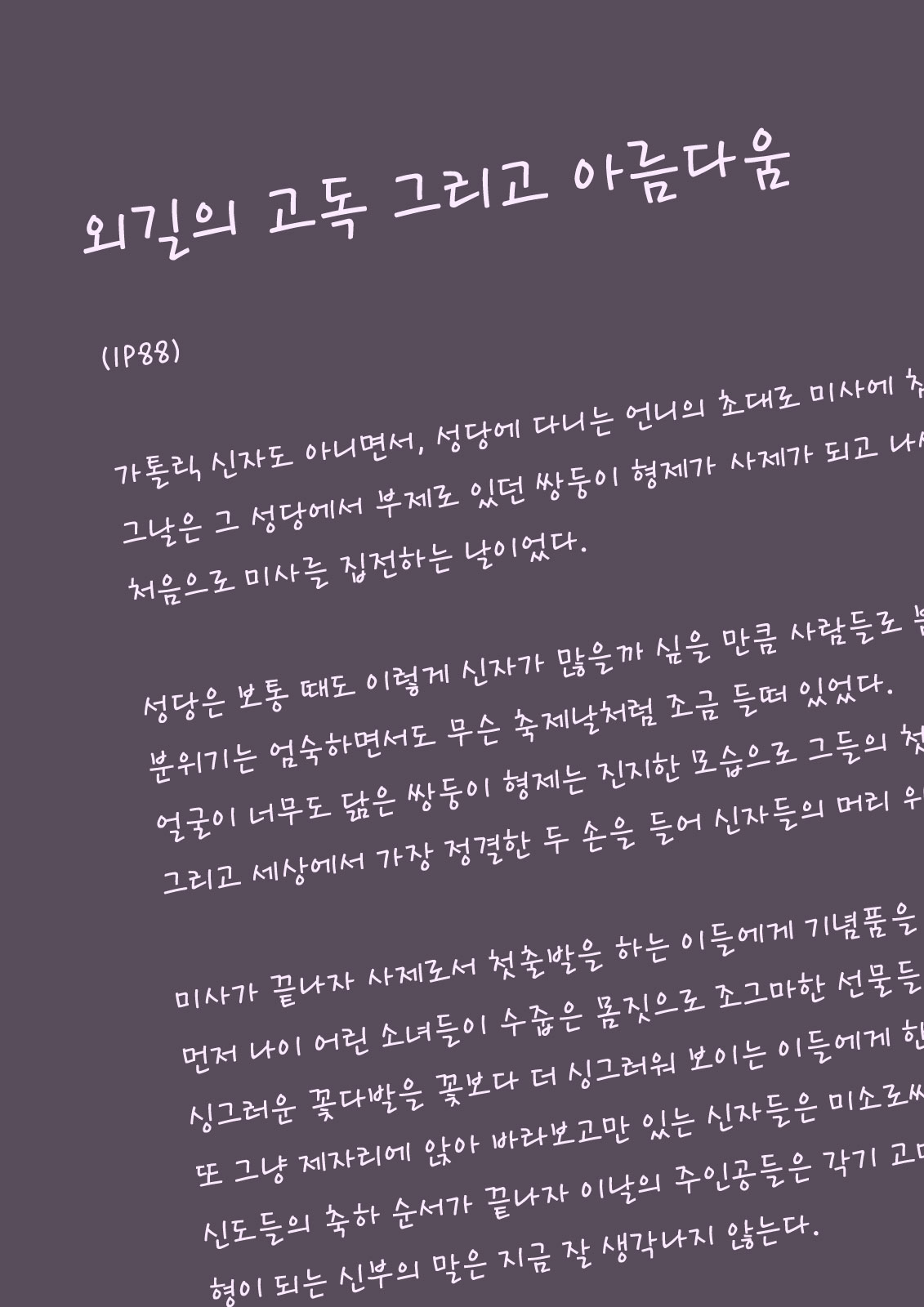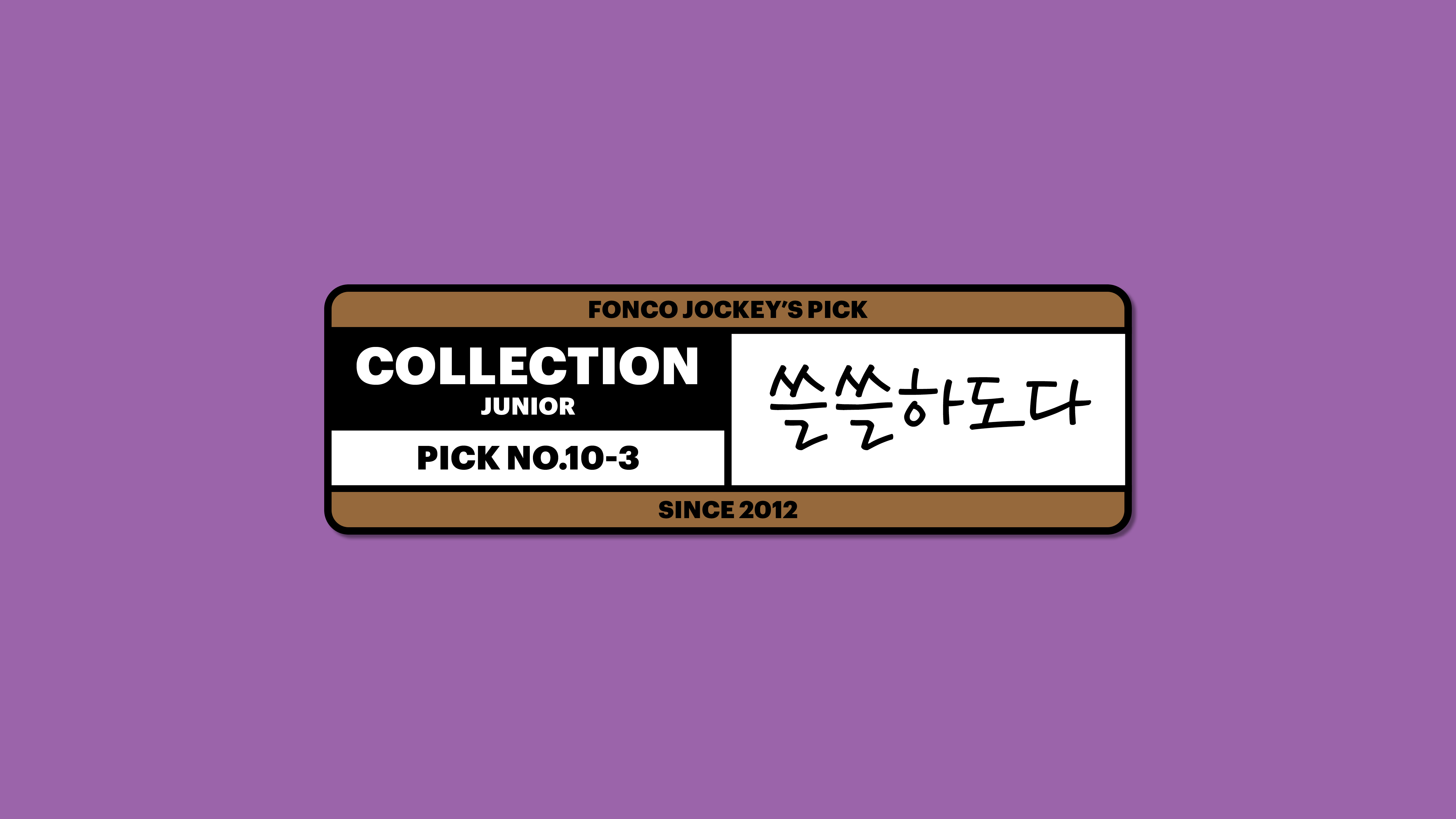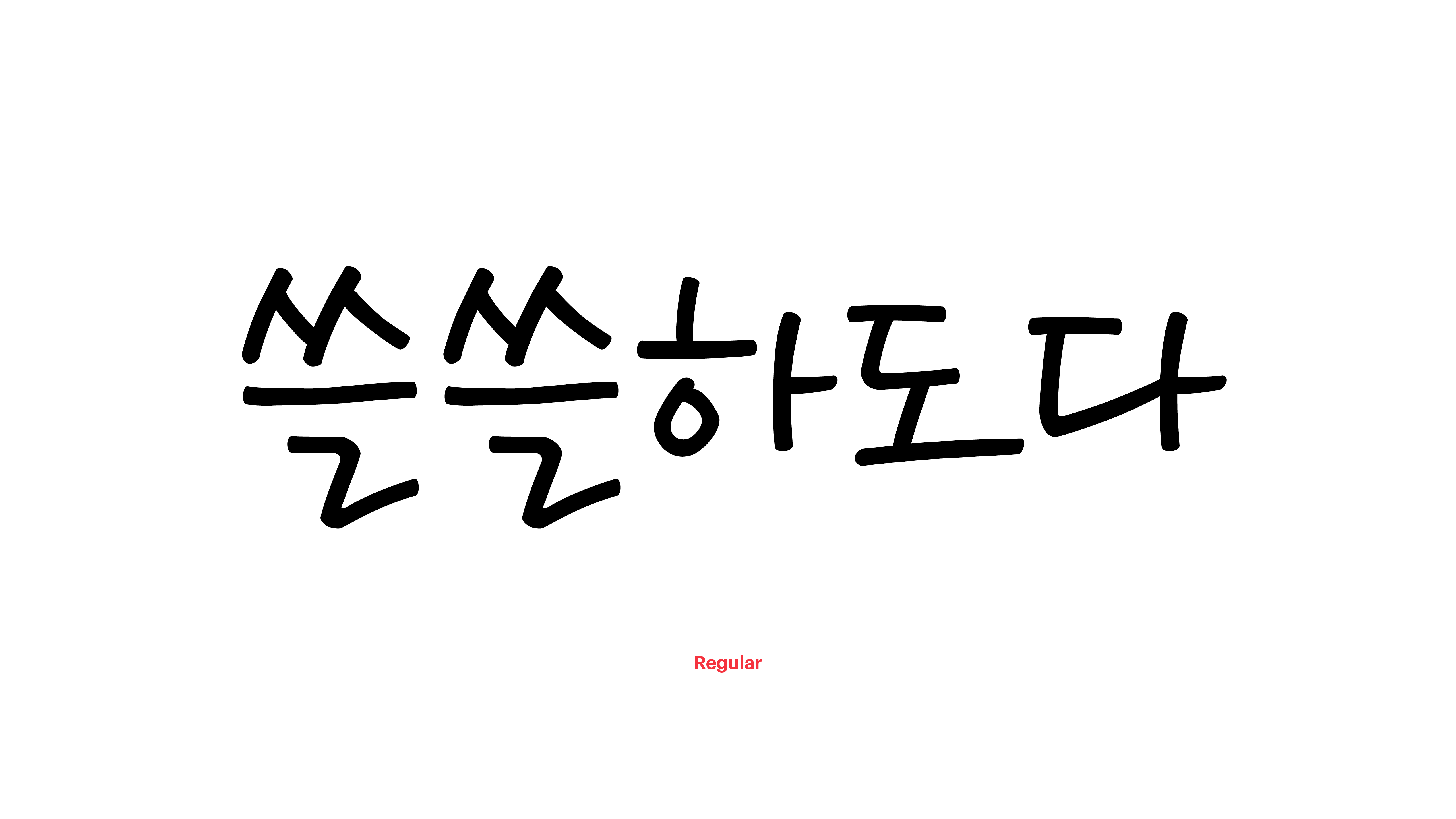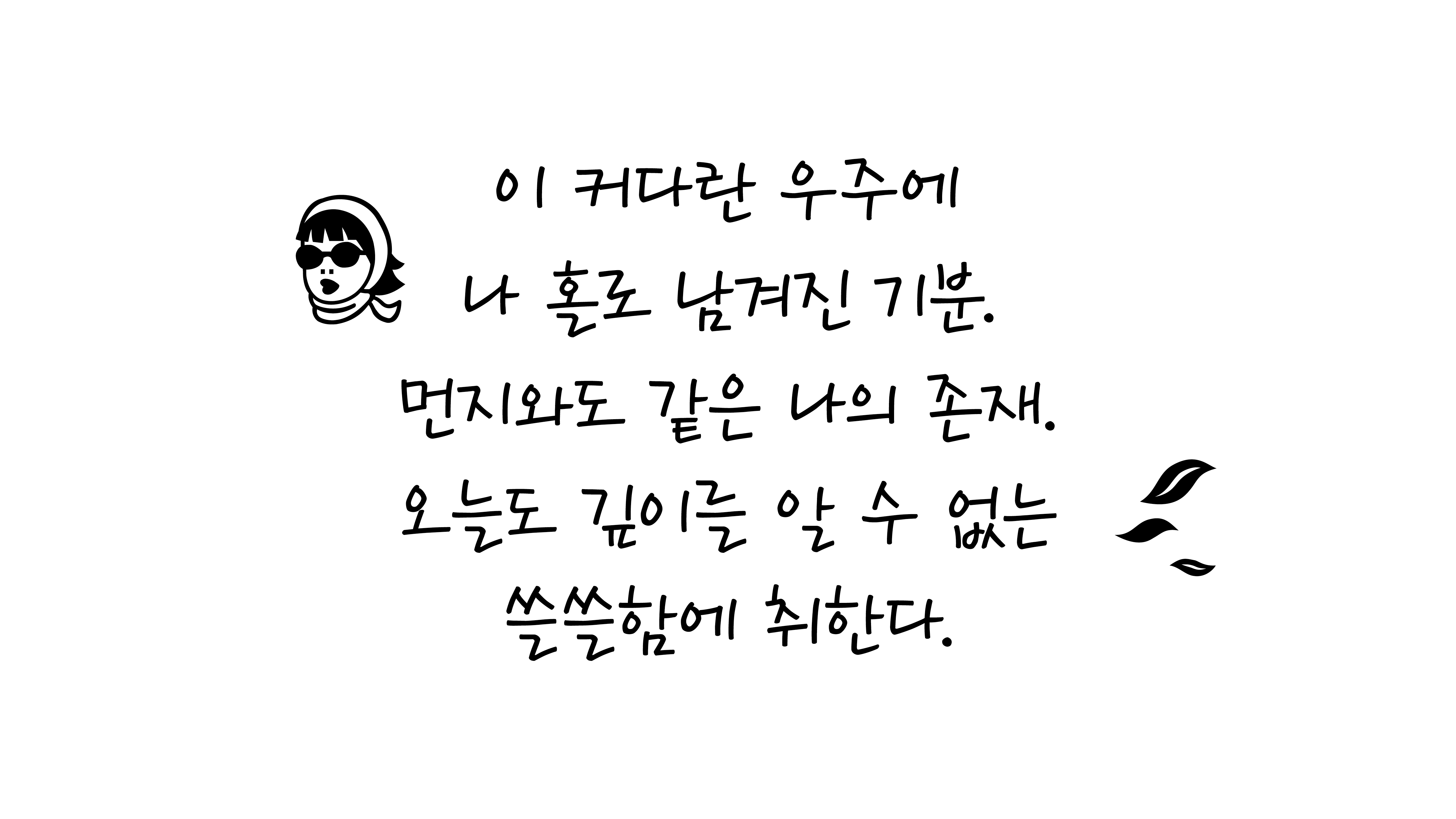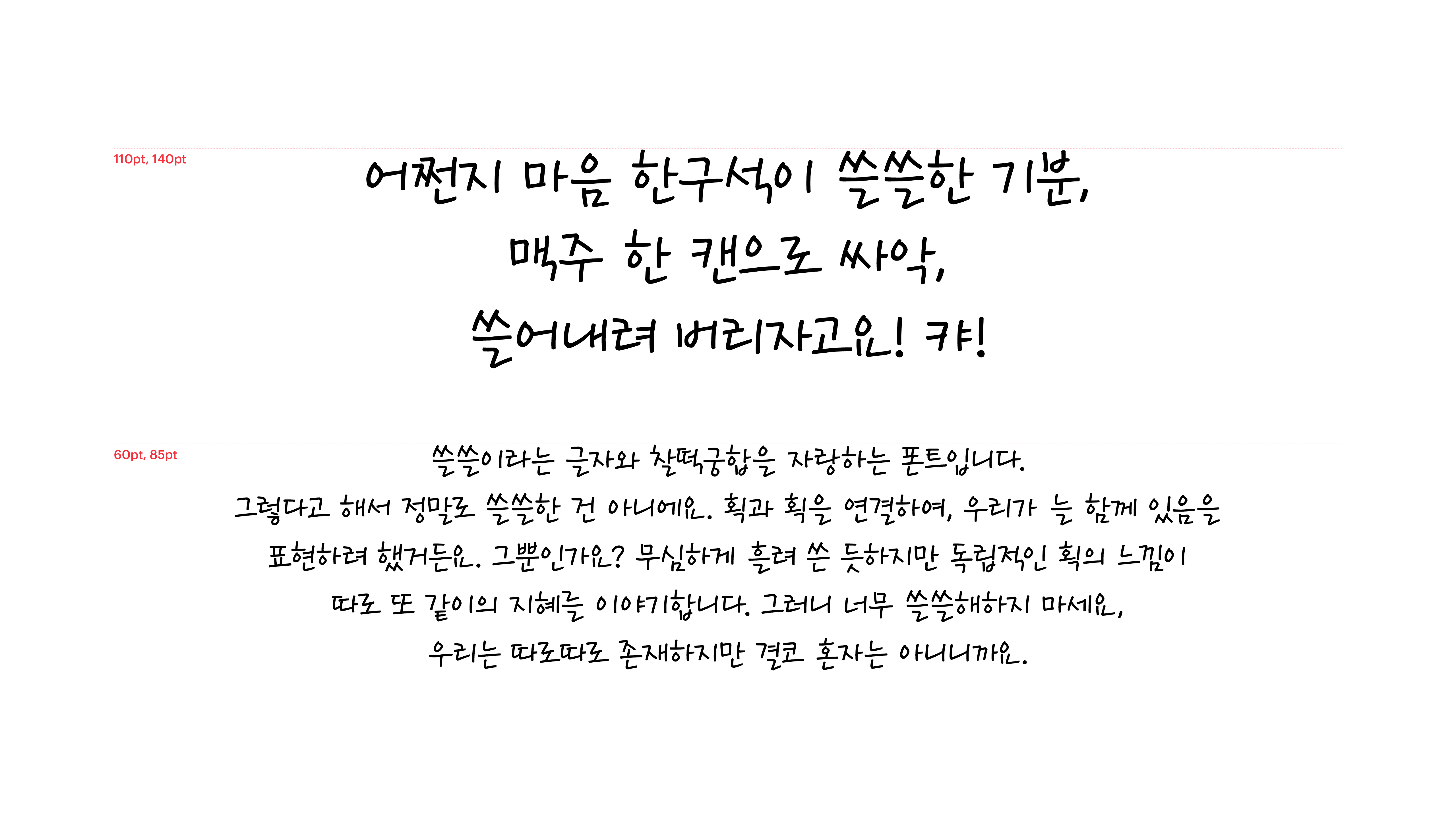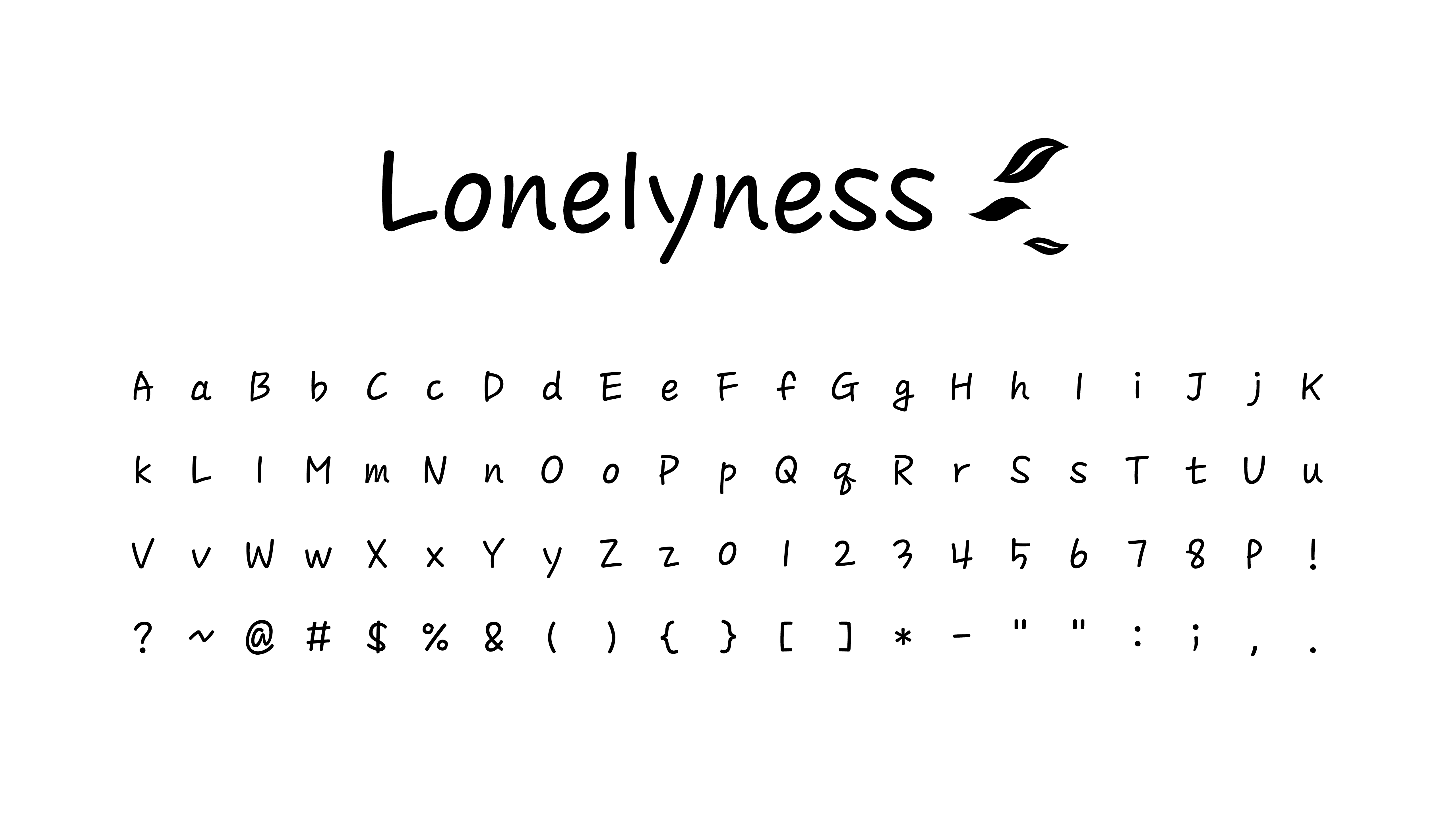
쓸쓸이라는 글자와 찰떡궁합을 자랑하는 폰트입니다. 그렇다고 해서 정말로 쓸쓸한 건 아니에요. 획과 획을 연결하여, 우리가 늘 함께 있음을 표현하려 했거든요. 그뿐인가요? 무심하게 흘려 쓴 듯하지만 독립적인 획의 느낌이 따로 또 같이의 지혜를 이야기합니다. 그러니 너무 쓸쓸해 하지 마세요, 우리는 따로따로 존재하지만 결코 혼자는 아니니까요.
Yoon 쓸쓸하도다